Cassandre dos Tipografía realizadas en París, ellas son Peignot y Bifur
Adolphe Jean Marie Mouron, más conocido como Cassandre, fue un icónico diseñador gráfico y cartelista francés de origen ucraniano. Revolucionó el arte del cartelismo con su estilo audaz y modernista.
Tanto Bifur y Peignot son dos tipografías creades en su periodo en francia, eran utilizadas en sus carteles.
Bifur
Bifur fue creada en 1929, es la primer tipografía por Cassandre para la fundición Deberny & Peignot, esta familia rompo con lo tradicional, muestra la faceta de diseñador cubista, ya que cada letra esta pensada como una unidad, cada una con su geometría y con luces y sombras bien plateadas, jugando con trazos gruesos, líneas finas y rupturas.
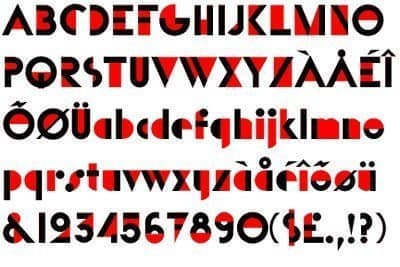
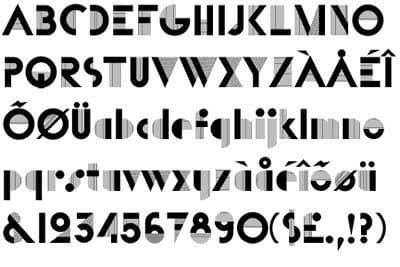
Peignot
Esta celebre tipografía Adolphe Jean Marie Mouron la crea en noviembre del año 1937 para la fundición Deberny & Peignot. Este alfabeto tiene varias particularidades que lo hacen único, tiene tres grosores distintos, las letras altas en minúscula como b, d, f, h, k, y la l, sus astas ascendentes son más altas que sus astas descendentes como la g o j. En las mayúsculas encontramos estos tres trazos de distinto tenor, en la A el ascendente es fino, el descendente del triangulo es grueso pero barra es aun más finas que el asta izquierda más fina.